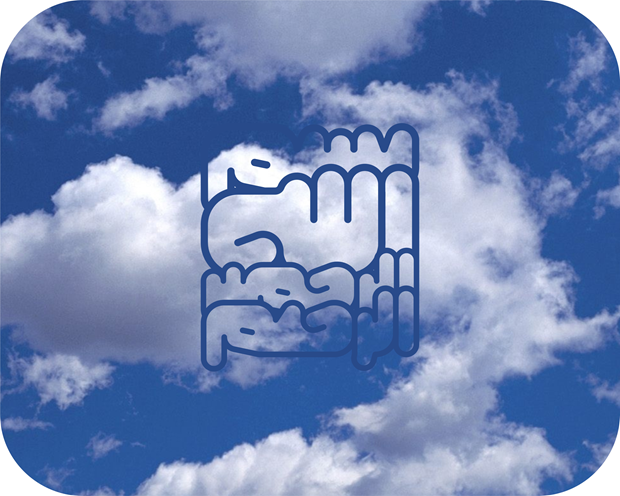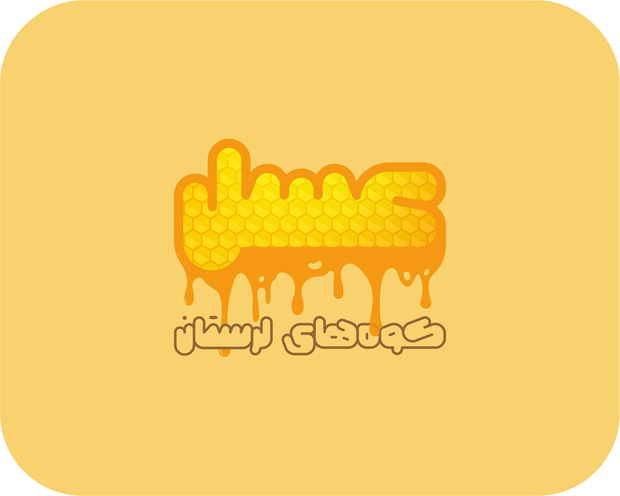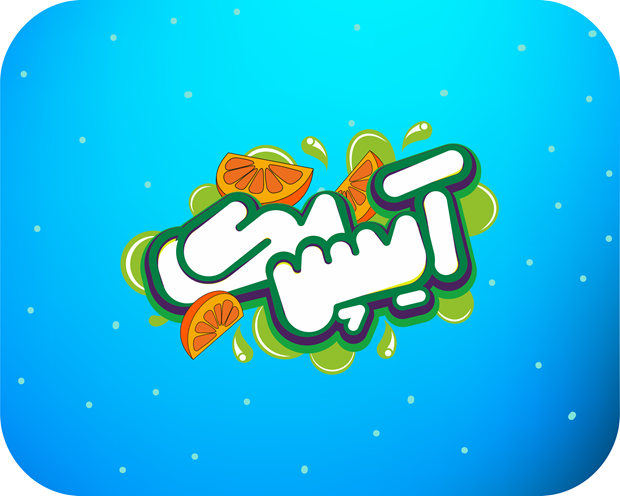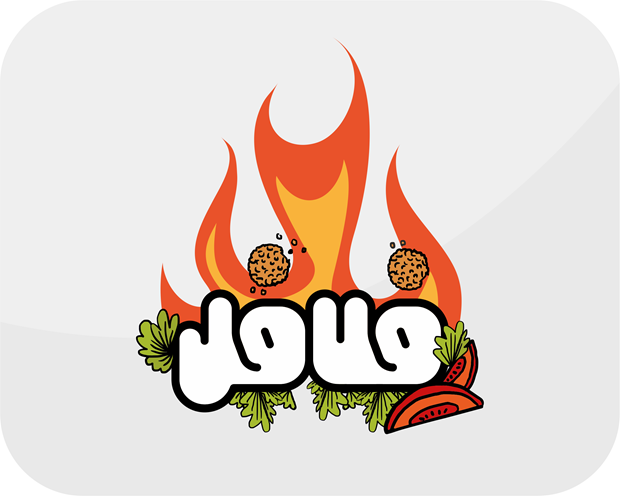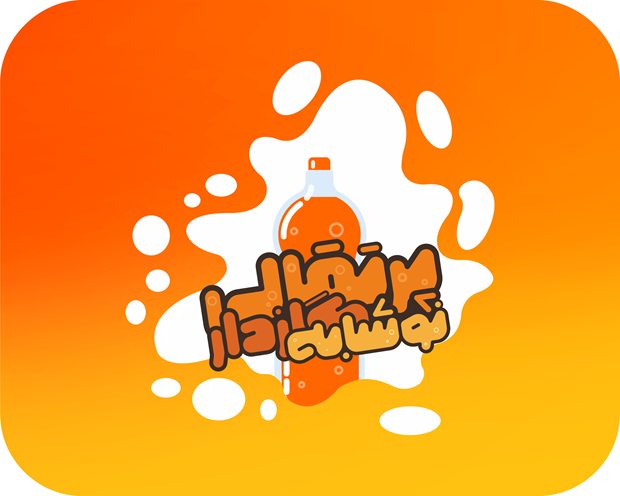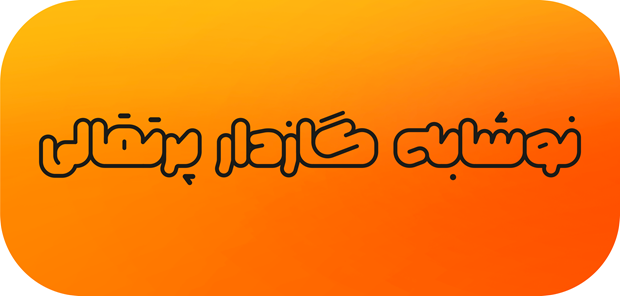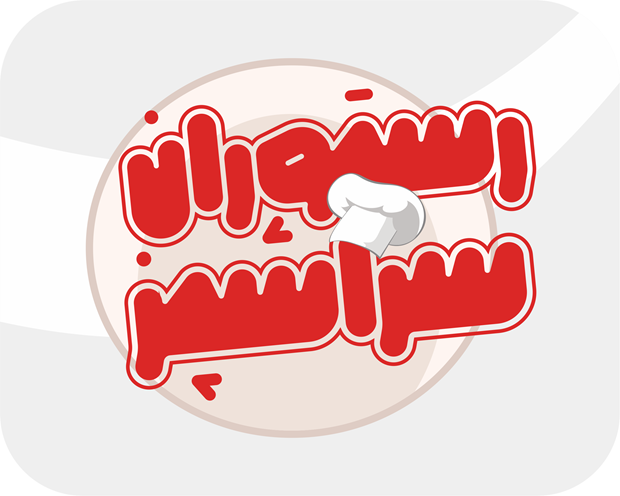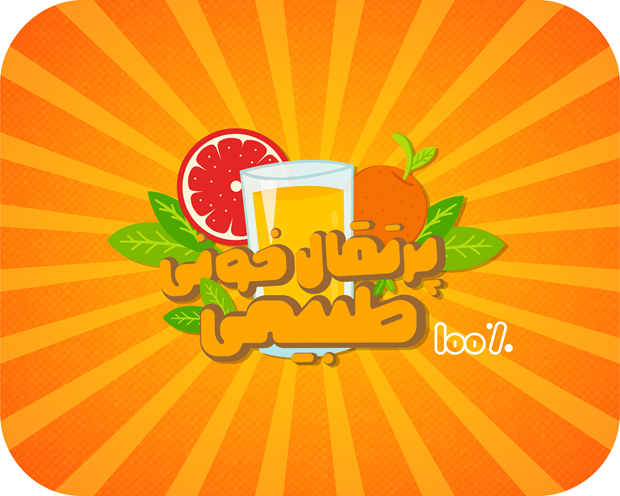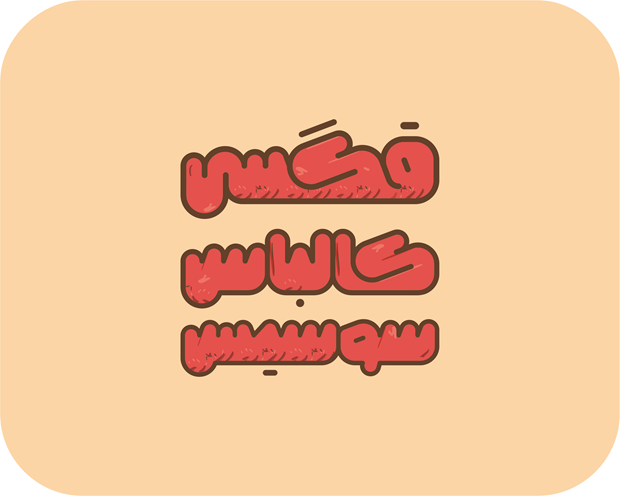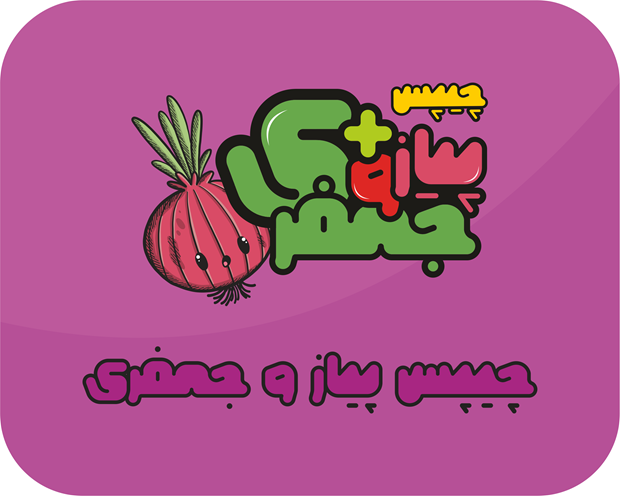
درباره قلم نرگس خاتون
تایپفیس خاتون از دسته تایپهای نمایشی و اوتلاین است که دارای خاصیت نمایش در تبلیغات محیطی و بستهبندی محصولات است. طراحی خاص کاراکترها و اوتلاین بودن این حروف فضای زیادی را برای ایجاد تغییرات مناسب هم در فضای بیرونی و هم در فضای محصور در کلمات فراهم کرده است تا با خلاقیت طراح در استفاده از این حروف به نتیجه دلخواه رسید. ارتباط بین خاتون و تصویر سازی از مهمترین خصوصیات این تایپ است جایی که یک پارچگی تصویر در کنار کاراکترهای پویا و شیرین خاتون حس خوب و دلپذیری به مخاطب خود میدهد. در بحث کرنینگ حروف (فاصله گذاری ) خاتون به شکل خاصی عمل میکند و با توجه به اوتلاین بودن آن بدون ضربه زدن به خواندن هر حرف، برای یک پارچگی و استحکام کلمات کاراکترهای تشکیل دهنده کلمات را به هم میچسباند و فقط کلمات هستند که از هم فاصله میگیرند...
حروف ترکیبی و حروف جایگزین طراحی شده برای این فونت امکان تایپ جذابتری در اختیار طراح قرار میدهد تا در نهایت طرحهای اثرگذارتری داشته باشد...
امیدوارم خاتون بتواند همراه قدرتمندی در جعبه ابزار گرافیک و طراحان کشور باشد....